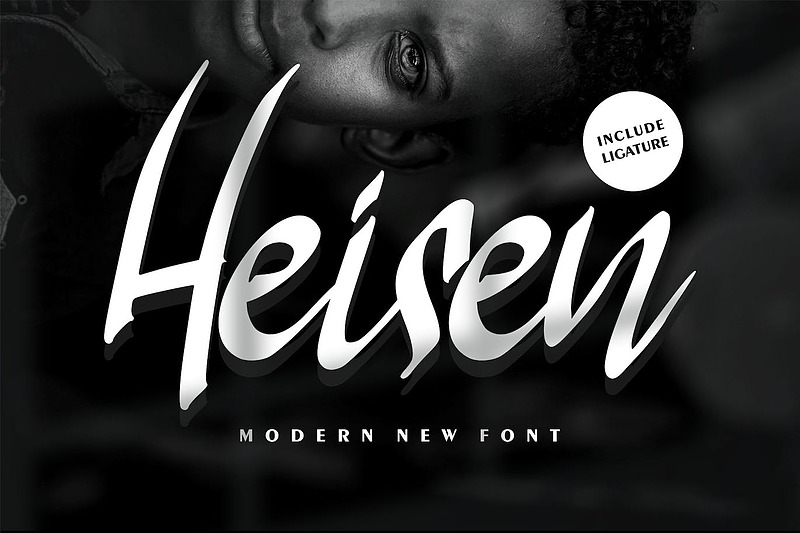
هایزن با سبک کالیگرافی، بسیار زیبا در دعوتنامهها مانند کارت تبریک، متریال برندسازی، کارت ویزیت، نقلقول، پوستر و موارد دیگر!
کاراکترهای آلترنیت یا جایگزین به چندین ویژگی اپنتایپ مانند استایلیستیک ستها، استایلیستیک آلترنیتها، کانتکسچوال آلترنیت، اسواشها و لیگچرها تقسیم شدند. ویژگیهای اپنتایپ را میتوان با استفاده از برنامههای هوشمند اپنتایپ مانند ادوبی ایلاستریتور، ادوبی ایندیزاین، ادوبی فتوشاپ، کورل دراو ایکس و مایکروسافت ورد مشاهده کرد. به این فونت یونیکد PUA داده شده (فونتهای کدگذاریشده خاص). به طوری که به راحتی میتوان به تمام کاراکترهای آلترنیت به طور کامل دسترسی داشت.
آلترنیتها و لیگچرها
اعداد و علائم نگارشی
فونت شامل پشتیبانی چندزبانه است
طبقهبندی: اسکریپت و دستنویس
اندازه بهینه: بزرگ (نمایش، پوستر)